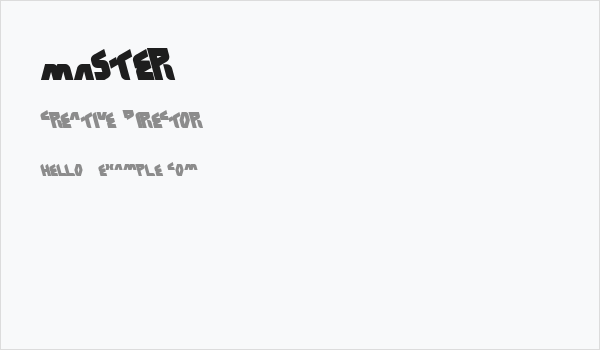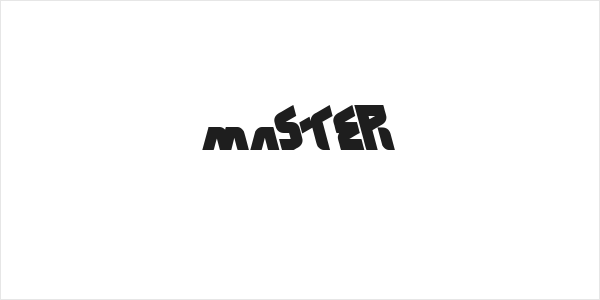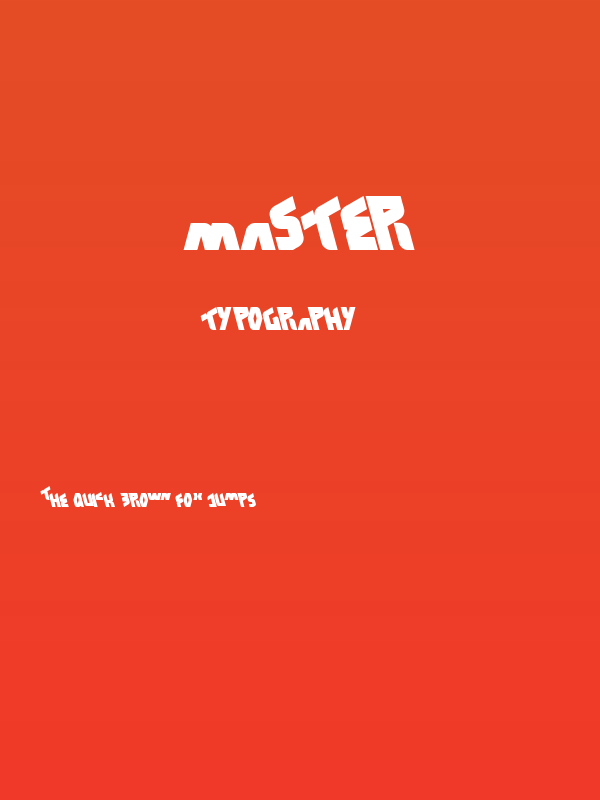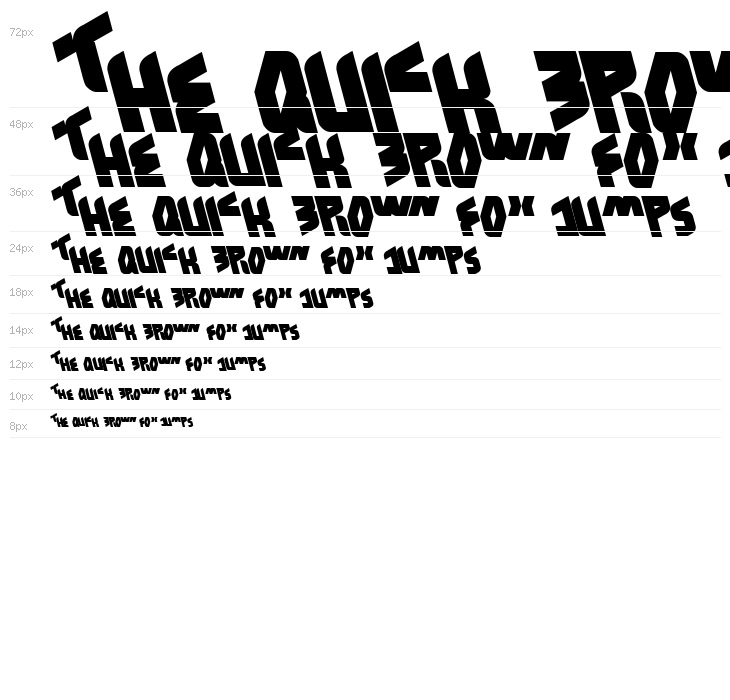
MASTER Font
| Stile generale | Futuristic, Modern |
| Progetti proposti | Ideal for sci-fi themed designs, video game titles, posters, and branding that requires a modern and edgy look. |